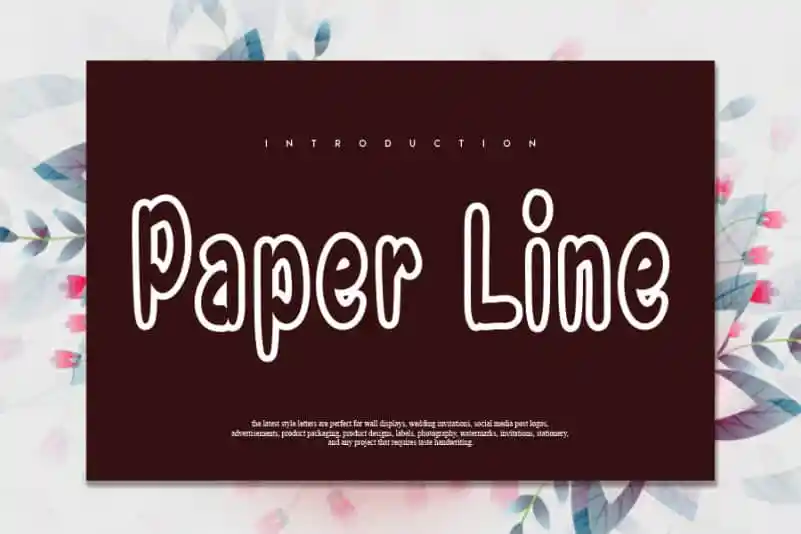
Paper Line Display Font – Download Grátis
A Paper Line Display Font é uma ótima escolha para quem procura um charme encantador no design digital. Esta fonte escrita a mão adere perfeitamente à categoria de Handwritten Fonts, trazendo um toque único e peculiar aos seus projetos. Ela é tão divertida que pode transformar qualquer ideia criativa em uma obra de arte instantânea. Essa elegante opção para exibição irá destacar suas criações com um brilho especial, tornando cada projeto mais especial e memorável. Se você busca adicionar um toque pessoal a seus designs semelhantes a uma conversa entre amigos, Paper Line Display Font é o elemento perfeito que você está procurando. Adicione esta fonte à sua lista de favoritos e observe como ela transformará suas ideias em verdades vivas.